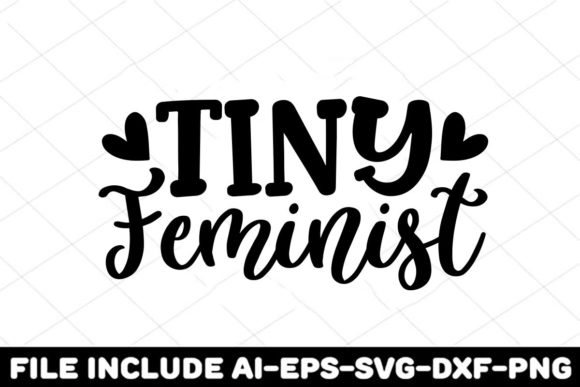
Tiny Feminist
Nếu bạn đang tìm kiếm các tài nguyên chất lượng cao như Tiny Feminist, gói cao cấp này là một lựa chọn tuyệt vời cho các dự án sáng tạo của bạn.
Được chế tác với độ chính xác cao, Tiny Feminist cung cấp các vector sạch, kiểu chữ mượt mà và giấy phép thương mại để bạn yên tâm.
Cho dù bạn đang tạo sản phẩm POD (In theo yêu cầu), thiệp mời đám cưới hay đồ họa mạng xã hội, Tiny Feminist đều là một sự lựa chọn lý tưởng.